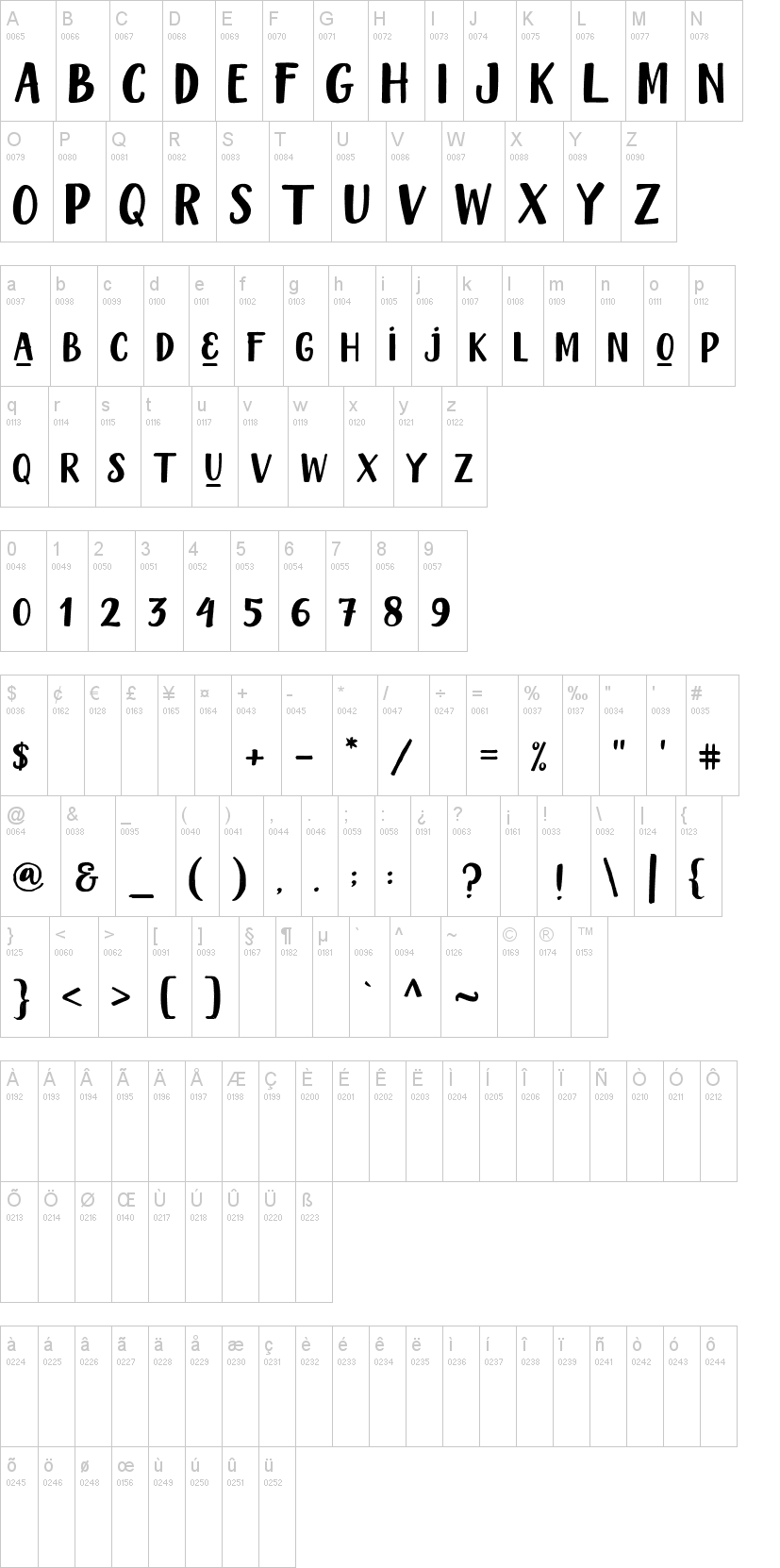
Chandelle Display 是一款现代化的抽象字体,由英国设计师 Stephen Miggas 创作。字体以均衡的线条和抽象的形状组合而成,拥有极佳的可读性和视觉效果。它的细节处理和完美的笔画曲线,让它具有极强的视觉冲击力,能够更好地吸引用户的眼球。Chandelle Display 字体可以用于广告、海报、标识等多种场景,能够带来更加精致的视觉体验。内容介绍
Chandelle Display是一款非常不错的手写艺术字体,具有很好的视觉感,适合于文化类的宣传设计、商业类品牌的广告和产品包装设计以及个性化文字排版等较多场景。